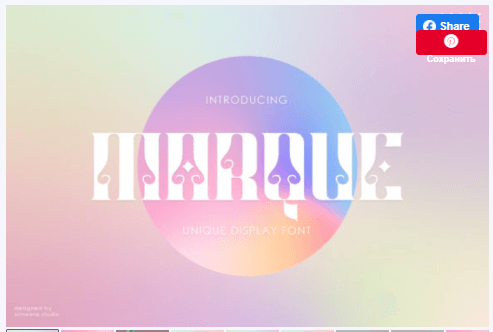
Marque Font
Marque - шикарный, детализированный и причудливый дисплейный шрифт. Он придаст изюминку любому дизайнерскому проекту, который вы желаете создать! Добавьте его уверенно в свои проекты, и результат вам понравится.